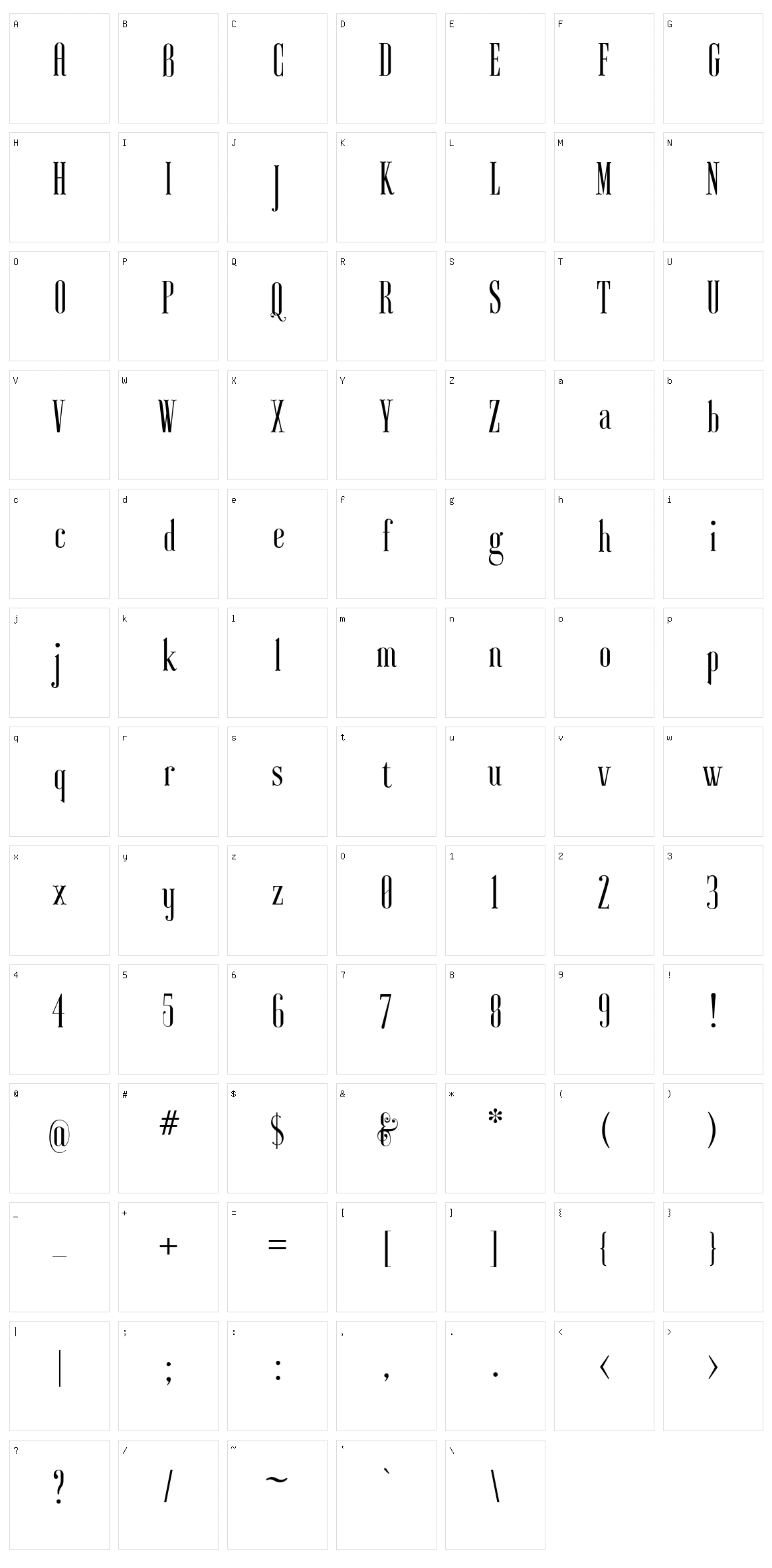
Ayres
Designed by: MAGOfonts
Category: Serif
Ayres typeface
Ayres es una fuente condensada, para su uso display.
Ayres typeface
Ayres is a condensed font, for display use.